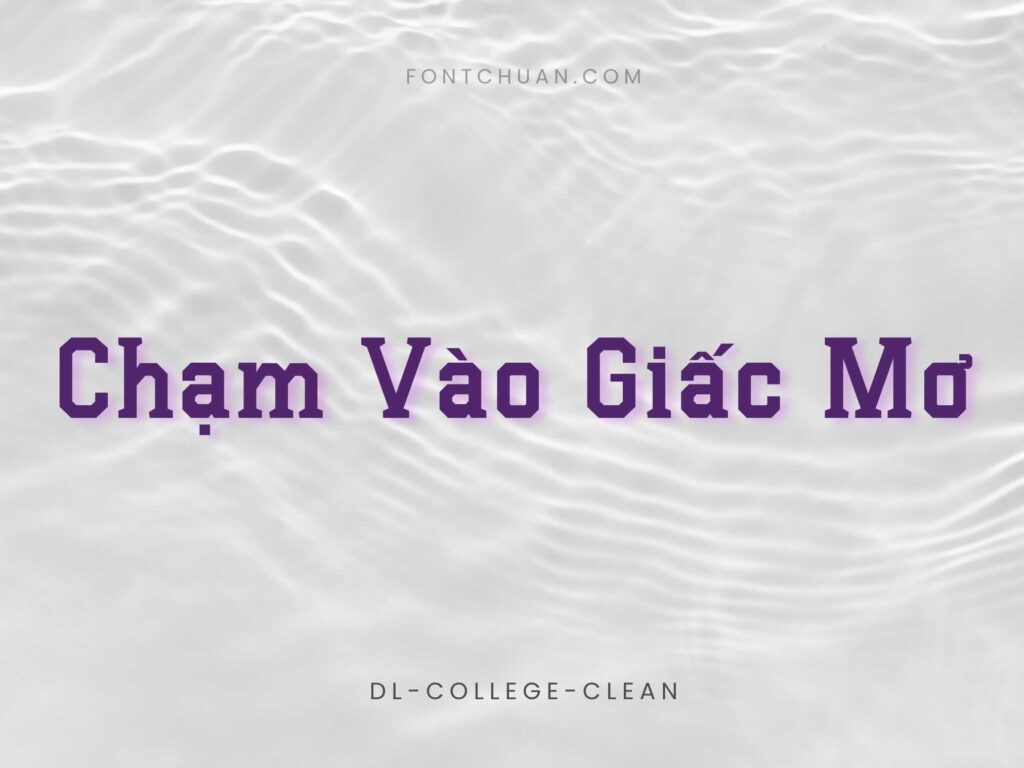
Font DL College Clean Việt Hóa
College Clean là một kiểu chữ mang phong cách cổ điển, được thiết kế bởi Galdino Otten Fonts. Font này thuộc thể loại Fancy với phong cách truyền thống, mang đến cảm giác chuyên nghiệp và mạnh mẽ. Đặc biệt, College Clean đã được Việt hóa bởi Tduy, hỗ trợ tiếng Việt cùng nhiều ngôn ngữ khác, đáp ứng nhu cầu đa dạng của người dùng. Font này được sưu tầm và đăng tải bởi thành viên của Font Chuẩn, giúp cộng đồng thiết kế dễ dàng tiếp cận và sử dụng trong các dự án của mình.
Về đặc điểm thiết kế, College Clean sở hữu các ký tự đậm, rõ ràng với đường nét sắc sảo, phù hợp cho các thiết kế như tiêu đề, poster, logo, bao bì sản phẩm và các ấn phẩm truyền thông cần sự nổi bật và chuyên nghiệp. Ngoài ra, College Clean còn thích hợp cho các ngành nghề như quảng cáo, giáo dục, công nghệ và bất động sản, cùng các sự kiện đặc biệt như lễ hội, sinh nhật, Halloween và Trung thu.